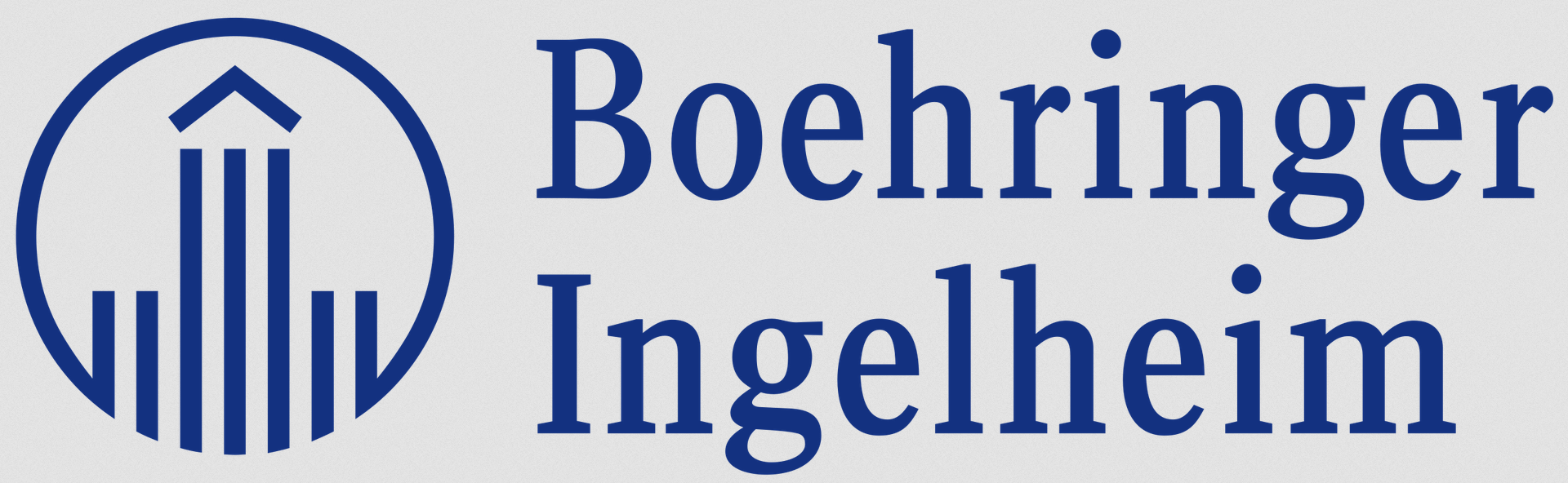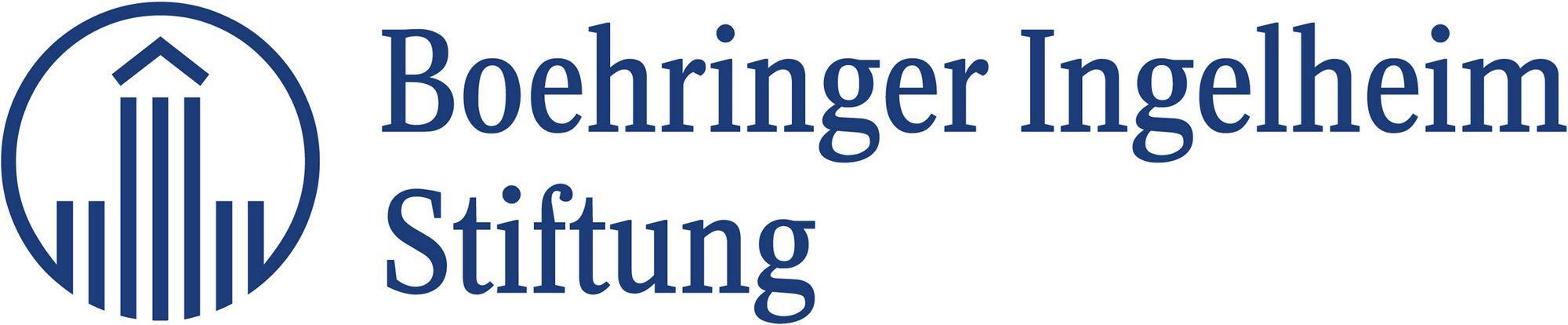
Suche Schrift aus Boehringer Ingelheim-Logo
weiß jemand, in welcher Schrift das Logo von Boehringer Ingelheim gesetzt ist? Oder, falls es ein Coustom-Font ist, auf welcher Schrift es basiert? WhatTheFont hat leider keine brauchbaren Ergebnisse ausgespuckt.
Im Rahmen des Redesigns erhält das Unternehmen mit der Boehringer Forward eine neue Hausschrift – diese löst die vom Typedesigner Ole Schäfer (1995 bis 1999 bei Metadesign) gezeichnete BI Sans) ab.
Aber keine Angabe zur Logoschrift …
Auch nur Textschrift … Logo in der Hierarchie links …
Vielleicht ist das nicht mal eine komplette (Satz-) Schrift?
Da fällt mir gerade die Plantin ein … Gibts die auch in Condensed?
Oder …
Nahe genug dran?
Danke Uwe! Tatsächlich habe ich diese Seiten auf der Suche nach der Schrift schon besucht. Leider wird die Schrift im Logo nie erwähnt.
Könnte natürlich durchaus sein, dass es keine komplette Satzschrift ist. Daher mein Kommentar zur Custom-Font. Kann mir aber schwer vorstellen, dass es dazu gar keine Vorlage gab.
Eine Schrift die der gesuchten nahe kommt, ist die Concorde Nova. Aber besonders der charakteristische eckige Tropfen am r passt nicht.
Danke, die Plantin geht auch in die richtige Richtung – zumindest was die Serifen angeht sieht es recht ähnlich aus.
Nach nochmaliger Recherche hab ich zwei Quellen gefunden die besagen, dass Ole Schäfer damals auch die Logoschrift selbst gestaltet hat. Ich würde jetzt einfach mal behaupten, dass der Ausgangspunkt dafür die FF Zine Serif Display war. Die passt bis auf einige (wahrscheinlich angepasste) Zeichen wirklich gut.